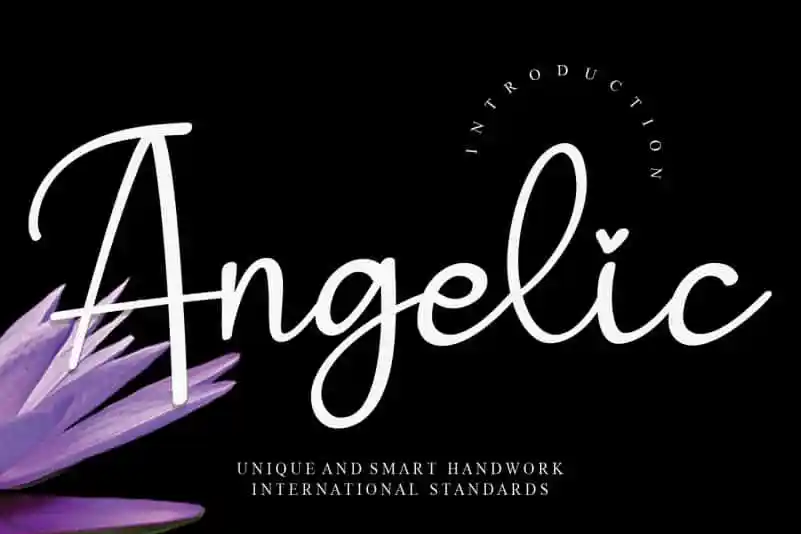
A ‘Angelic Handwritten Font’ é uma elegante escolha para quem procura adicionar um toque de romantismo e delicadeza a qualquer projeto visual. Desenvolvida pelo designer creativeletter, essa fonte cuidadosamente criada oferece linhas sutis e traços delicados que transmitem uma sensação suave e encantadora. Perfeita para nomes, mensagens personalizadas ou até mesmo gráficos de celebridades, a ‘Angelic Handwritten Font’ traz sua própria graça ao texto em um estilo que se move entre o elegante e o íntimo. Ideal tanto para enfeitar websites quanto para imprimir no papel, essa fonte é uma ótima opção para quem procura dar vida à mensagem através de um visual delicado e memorável. Engane-se só por um momento ao escrever com ela – você se sentirá imediatamente envolvido em sua própria experiência criativa.